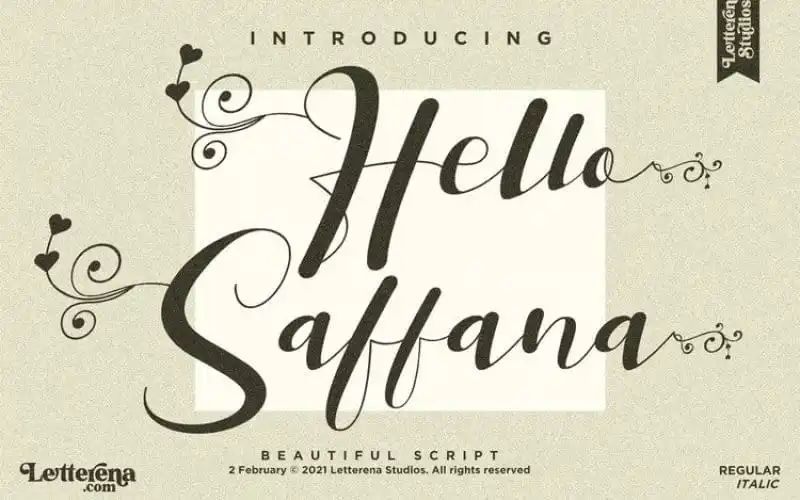
Hello Saffana Calligraphy Font – Download Grátis
A fonte “Hello Saffana Calligraphy Font” é uma criação moderna inspirada na elegante escrita clássica que se destaca por sua qualidade perfeita e atmosfera contemporânea. Perfeita para projetos variados como logotipos, identidades de marca, design de móveis de casas, embalagens de produtos, chávenas, frases decorativas, cartazes, bolsas de presente, camisas personalizadas, capas de livros, cartões de nome, convites e cards de aniversário, sacos de shopping, imagens fotográficas, marcas únicas ou eventos especiais. Este novo fonte elegante e sofisticado é a escolha perfeita para qualquer projeto que deseje um toque delicado e refinado do script na sua marca ou produto.